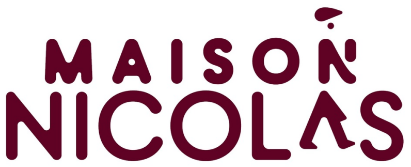
La typographie qui incarne l’élément identifié par les mots : exemples contemporains
Alors que, sur ce site, les exemples d’usage inventif de la forme des caractères correspondent généralement à des marques assez anciennes (série 1, série 2, série 3, hors-série spécial cyclimse), deux cas de figure récents montrent également la créativité des typographes.
marque française n°5196912
L’agence 181 Degrés a signé la nouvelle identité visuelle de Nicolas, qui profite de l’occasion pour faire évoluer son identité en « Maison Nicolas« , un retour aux sources.
Le personnage, formé par la superposition du N et du A, pourrait être un clin d’œil à Nectar, le « gentleman livreur » à l’allure ébahie des affiches publicitaires. Créé en 1922 par Dransy, ce personnage fut accompagné de son fils Glou-Glou et de sa femme Félicité.
marque de l’Union Européenne n°018703890
La marque semi-figurative mont Saint-Michel est l’élément emblématique de la refonte de l’identité visuelle, initiée par l’Établissement Public National du mont. Graphéine a conçu cette marque institutionnelle, avec l’appui de la fonderie Blaze Type qui a travaillé sur la typographie. L’accent sur le travail typographique fait écho à la présence de moines copistes dans l’abbaye du mont (dont une bibliothèque virtuelle est le témoin).
Saluée début 2026 (La Réclame, Stratégies, David Baulieu, Basti Sans MS, HD Graphisme), ce logo est le fruit d’un long processus. Comme expliqué dans le podcast de Graphéine, le travail de l’agence a commencé en 2021 et on a d’ailleurs pu voir ce logo de type « mot-image » dès le mois de mai 2022 (Ouest France, EPN du mont Saint-Michel, APIE).